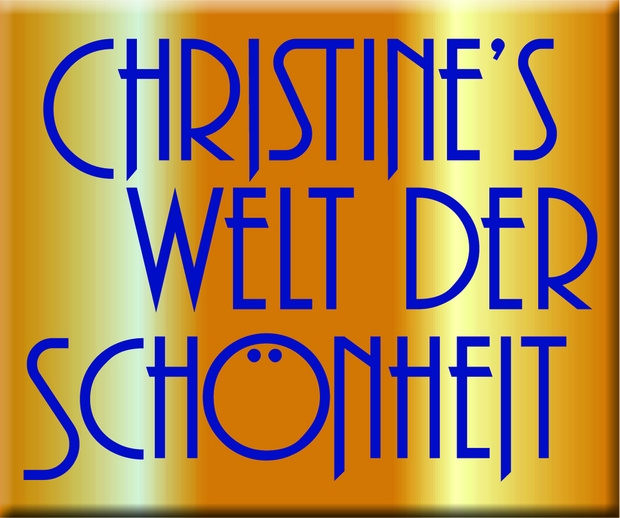
Schrift unauffindbar. Bitte um Hilfe.
Ich habe mir vor Jahren einmal dieses Logo für meine Mutter entworfen (ja ich weiss, es ist nicht sehr schön, aber sie will es behalten), leider habe ich diese Schriftart nicht mehr und weiss auch nicht wie sie heisst.
Vielleicht könnte mir hierbei jemand helfen, ich habe schon alle Font-Webseiten für Stunden abgeklappert, jedoch dieses Ö mit den Punkten IM Buchstaben nirgends finden können.
Ich kann Dir nicht ad hoc sagen, welche Schrift das ist, aber unter diesem Link findest Du diverse sehr gute Tipps zur Identifikation von Schriften zusammengestellt.
Und, wenn ich Dir noch einen Tipp geben darf: Wenn das Logo so beibehalten werden soll, dann würde ich zumindest den Apostroph rauszunehmen, da das Genitiv-s im Deutschen nur in wenigen begründeten Ausnahmefällen durch eine Apostroph abgetrennt werden darf.
Der Duden sagt dazu: »Normalerweise wird vor einem Genitiv-s kein Apostroph gesetzt.«
Als Beispiel für eine Ausnahme wird »Andrea’s Blumenecke« genannt (Zur Unterscheidung vom männlichen Namen Andreas)
Da eine solche Verwechslungsgefahr bei »Christine« nicht gegeben ist, solltest Du auf den falsch gesetzten Apostroph verzichten. :-)
Relativ dicht dran sind die ITC Anna und die Avenida von Linotype. Wenn Du diese beiden Schriften als Ausgangspunkt für Deine Suche nimmst und Dir dann bei den Schriftenhändlern ähnliche Schriften anzeigen lässt, dann könntest Du über diesen Kniff eventuell auf Deine Schrift stoßen.
Plaza Swash würde ich aufgrund der unterschiedlichen Buchstabenlängen sagen. Eventuell die Ö-Pönkte selbst nach innen gestellt?
Plaza Alternate hat auch die unterschiedlichen Formen.
Danke vielmals für die Hinweise und Anregungen. Im Endeffekt war es eine Mischung aus Plaza und Plaza Swash. Bezüglich des Apostroph habt ihr natürlich recht. Das wurde von mir ausgebessert und hat nichtmal in der alten Rechtschreibung (aus der ich noch stamme) gestimmt.